#20 quebrando as regras da tipografia
aqui na makers eu tento mesmo não falar demais de um mesmo assunto dentro do design, mas tem coisa que não dá pra fugir. uma dessas coisas é a tipografia: afinal, ela está em todo lugar, até aqui, nesse e-mail: repare que o título é enorme, o subtítulo é num cinza mais claro, às vezes eu uso maiúscula, às vezes não. mas eu ainda tento sair um pouco do básico nas edições... porque afinal, se você é designer ou um estudante de design, você conhece as regras do bom uso, ou vai conhecer logo, e eu não preciso ser quem vai te ensinar isso. então, por que não partir logo pra parte mais legal, e conhecer o trabalho de quem está fazendo algo diferente e inspirador?
Os pôsteres de Jessica Svendsen
Jessica Svendsen é uma designer que atua nas áreas de identidade visual e design editorial, e eu me apaixonei à primeira vista pelo seu trabalho tipográfico. Dá pra entender o porquê se você der uma olhada nessa série de pôsteres que ela produziu enquanto trabalhava no Pentagran, para a Universidade de Yale (onde ela estudou, inclusive). Sobreposições, quebra de texto inusuais, uso de sombras e elementos 3d, letras estreitas demais, largas demais… Escolhas que fariam alguns designers, mais tradicionais, torcerem o nariz. Mas justamente ao quebrar diversas “regras” da tipografia, Jessica cria visuais interessantes e inspiradores.
Jessica passou oito anos estudando na Universidade de Yale e ela começou na graduação de Inglês/Literatura; foi lá que começou a se interessar pela relação entre o texto e as letras que o compõem. Ela fala sobre isso em uma entrevista para o blog Ligature:
“Percebi que a forma poderia não apenas iluminar o significado do texto, mas também criar novos significados.
Em algumas das residências de Yale, há estúdios de tipografia totalmente equipados no porão. Ao definir o tipo, letra por letra, comecei a entender a relação entre o textual e o visual. (…)
Enquanto estudava Inglês, estudei principalmente literatura modernista. Eu me atraía pelos modernistas porque eles usavam significantes visuais para desfamiliarizar o leitor. Eles experimentaram como tipografia, composição e design de livro poderiam fazer parte da narrativa.”
O valor do design multi-tipográfico
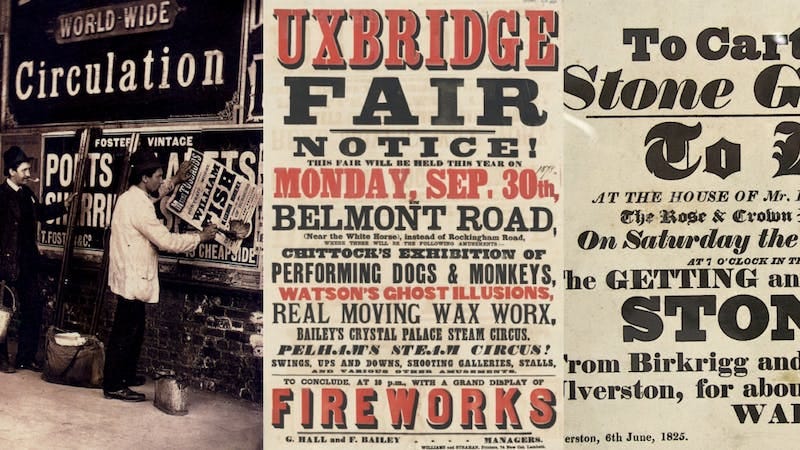
“O ideal é usar duas tipografias por layout, no máximo três.” Uma básica para os textos corridos, uma display pra chamar atenção e uma terceira pra situações especiais. Certo?
Errado, de acordo com a brilhante Bethany Heck. Ela escreveu o artigo “The Value of Multi-Typeface Design”, que foi traduzido e publicado no blog da Plau como “O valor do design multi-tipográfico”.
“Não confunda preferências com regras.
Não deixe a opinião de um designer afetar a forma como você resolve um problema. Tendo o conteúdo certo e as fontes certas, qualquer número de fontes pode funcionar num projeto. Costumo achar que os designers estão tentando impor suas opiniões estéticas quando argumentam a favor dessas limitações, ao invés de pensarem no bem do usuário de fato. Não acho que sua avó esteja preocupada com o número de fontes que existem nos livros de receita dela. Isso porque sua avó é sábia.
Não crie para outros designers, crie para o seu público.”
Eu já sou uma pessoa naturalmente atraída por soluções visuais mais criativas e mais complexas, mas até sobre isso o artigo da Bethany desmistifica alguns pontos. Porque dá pra usar várias fontes em um layout minimalista. Já ouviu falar que parear duas fontes muito semelhantes é ruim porque faz o leitor achar que as pequenas diferenças são erros? Bethany mostra que nem sempre. O design multi-tipográfico pode te levar a soluções que exploram o contraste e também a outras que exploram a semelhança.
A autora também analisa diversos casos e layouts tipográficos, trabalhos dela mesma e de outros designers. O artigo começa questionando essas “regras” sem nenhum fundamento real, e acaba se tornando em uma espécie de guia de possibilidades. Vale a leitura :)